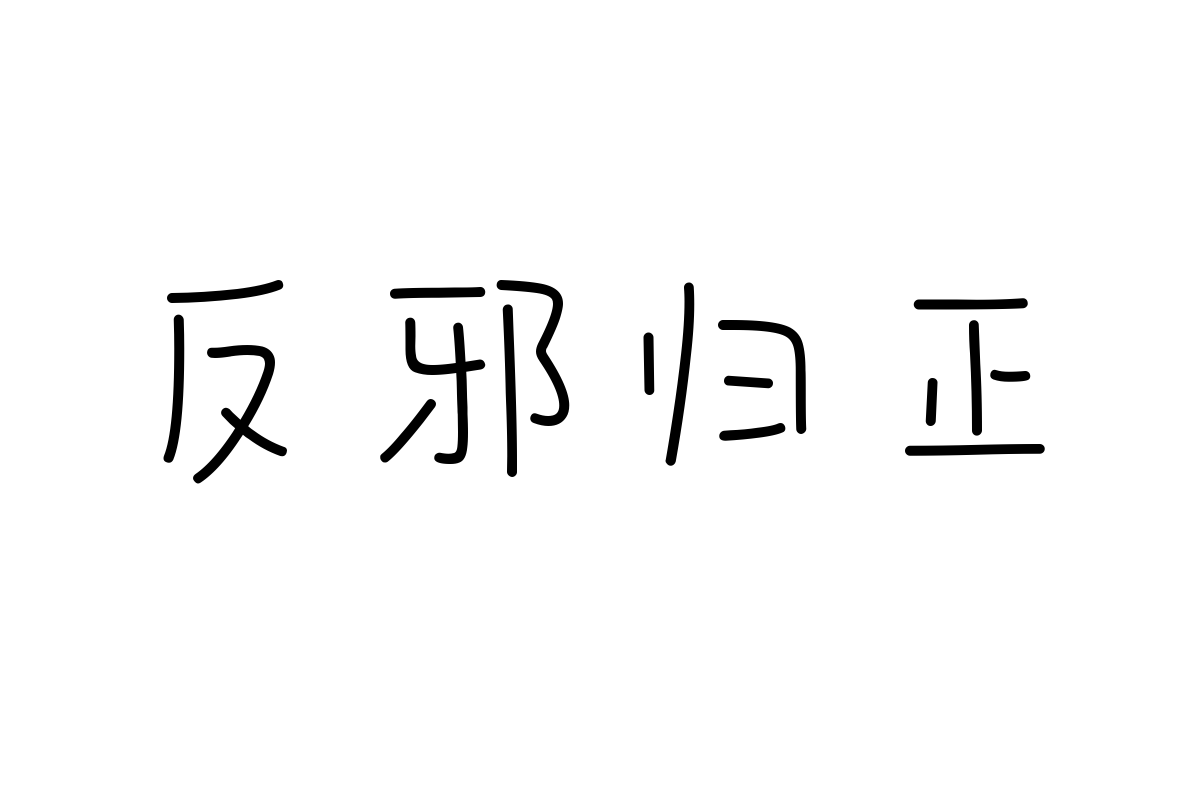
造字工房漫语体是一款独特的字体,它结合了现代和传统的元素,创造出了一种全新的视觉体验。这款字体的特点是:
1. 字形独特:造字工房漫语体的字形设计独特,线条流畅,结构紧凑,给人一种简洁、明快的感觉。
2. 风格多样:这款字体适用于各种场景,无论是正式的商务文件还是轻松的休闲文字,都能展现出其独特的魅力。
总之,造字工房漫语体是一款集美观、实用于一体的字体,无论是个人使用还是商业用途,都能满足您的需求。